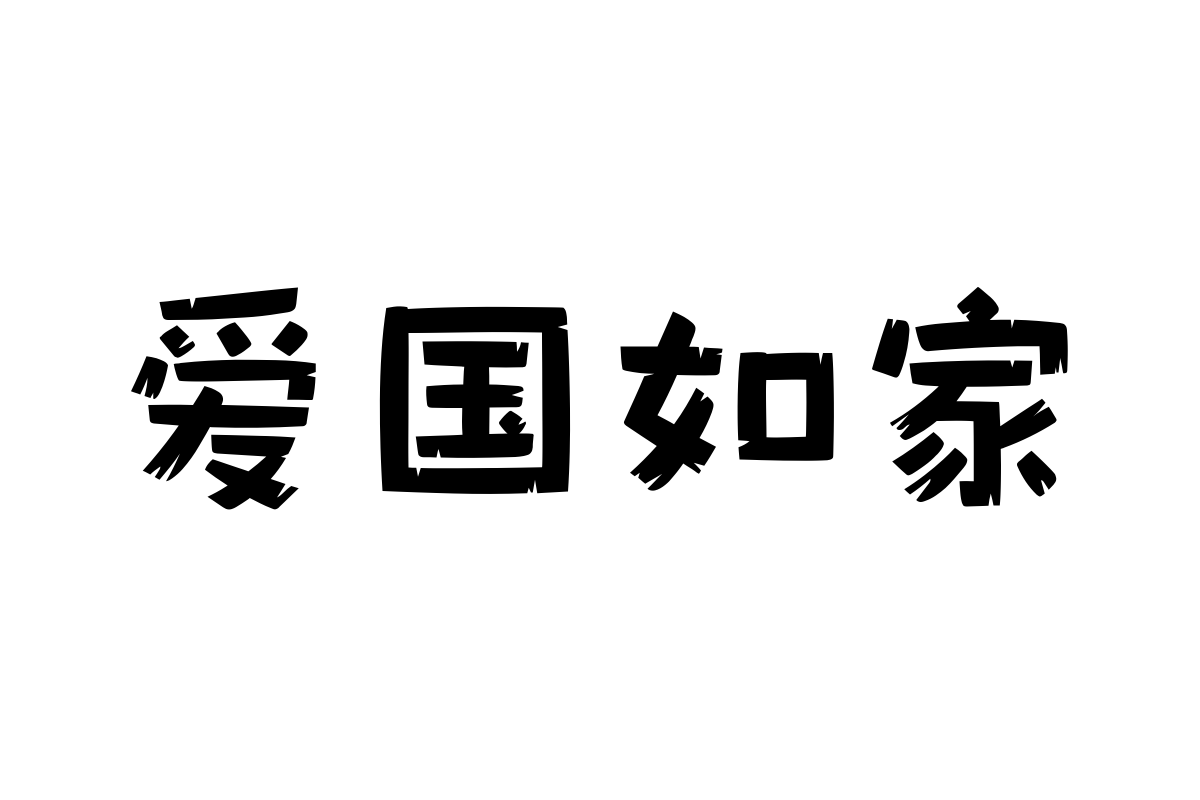
汉仪风波小木屋是一款现代简约风格的中文字体,具有独特的艺术感和设计感。这款字体采用了简洁的线条和形状,以及柔和的色彩搭配,给人一种轻松、舒适的感觉。同时,字体中还融入了一些抽象的元素和装饰性的细节,使得整体效果更加独特和有趣。
这款字体适用于各种设计场景,包括广告、海报、包装等。无论是用于品牌标识、产品名称还是文字内容,都能展现出独特的魅力和风格。此外,汉仪风波小木屋还提供了多种字形和字重选择,满足不同设计师的需求和喜好。